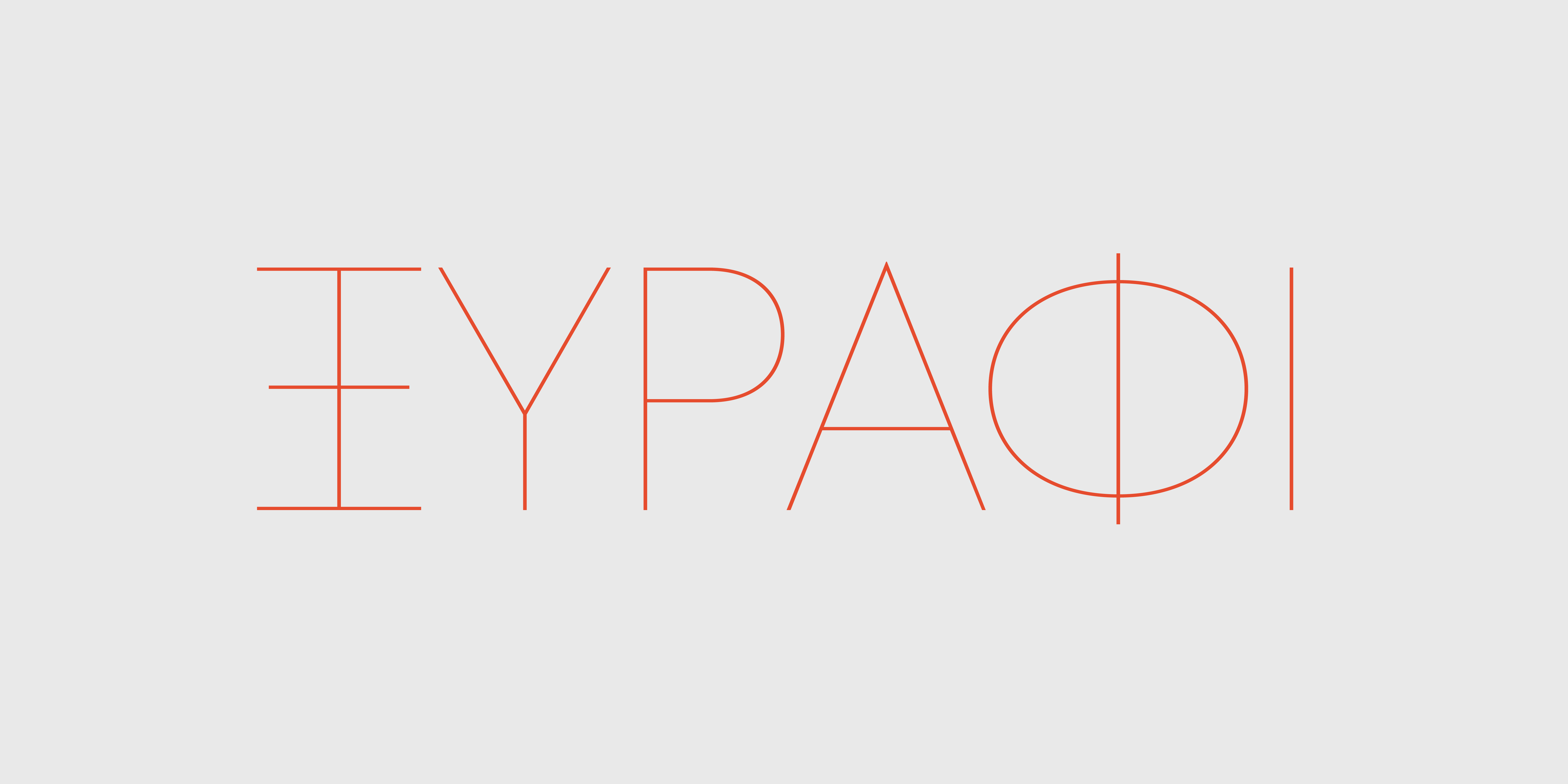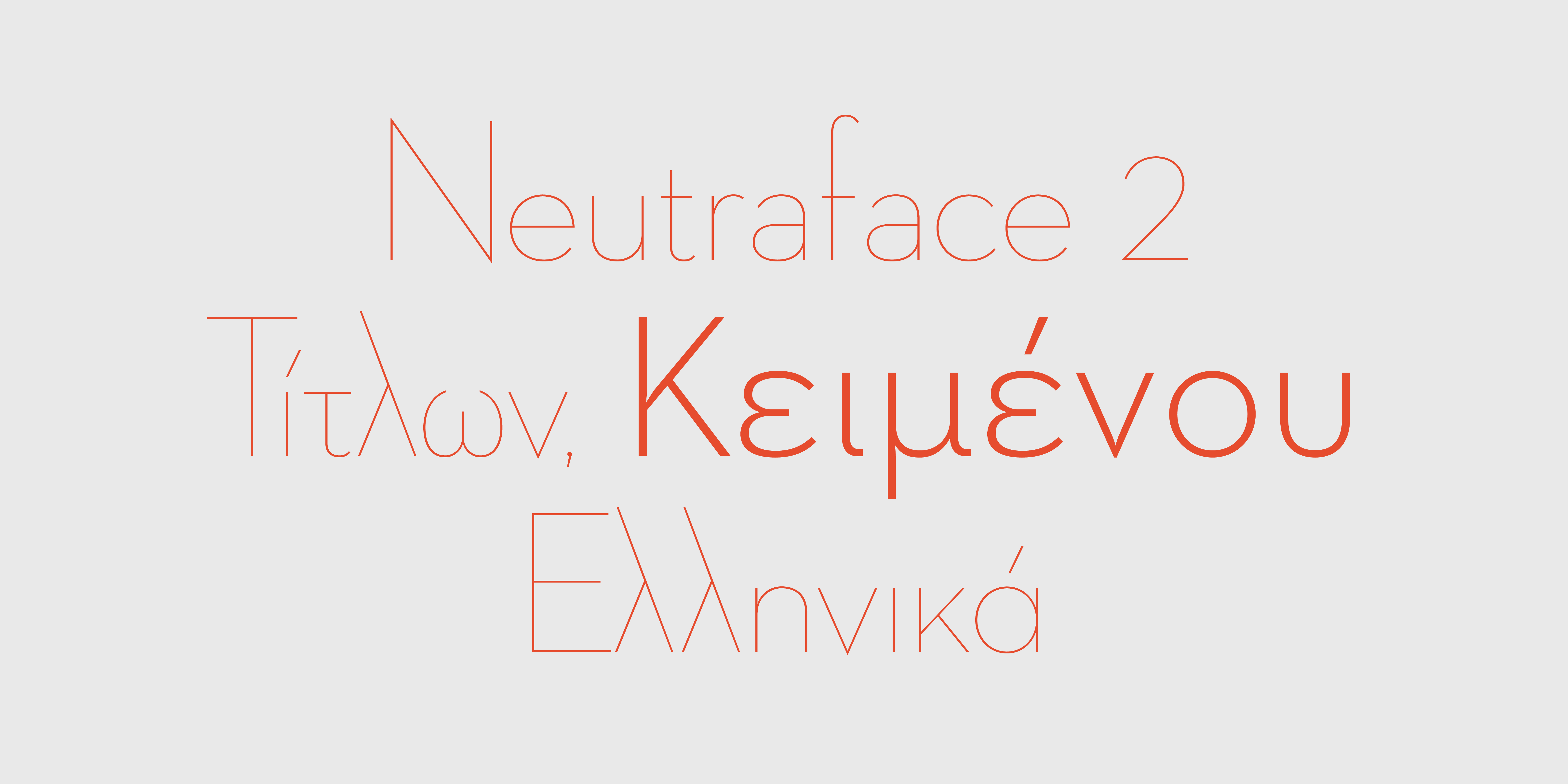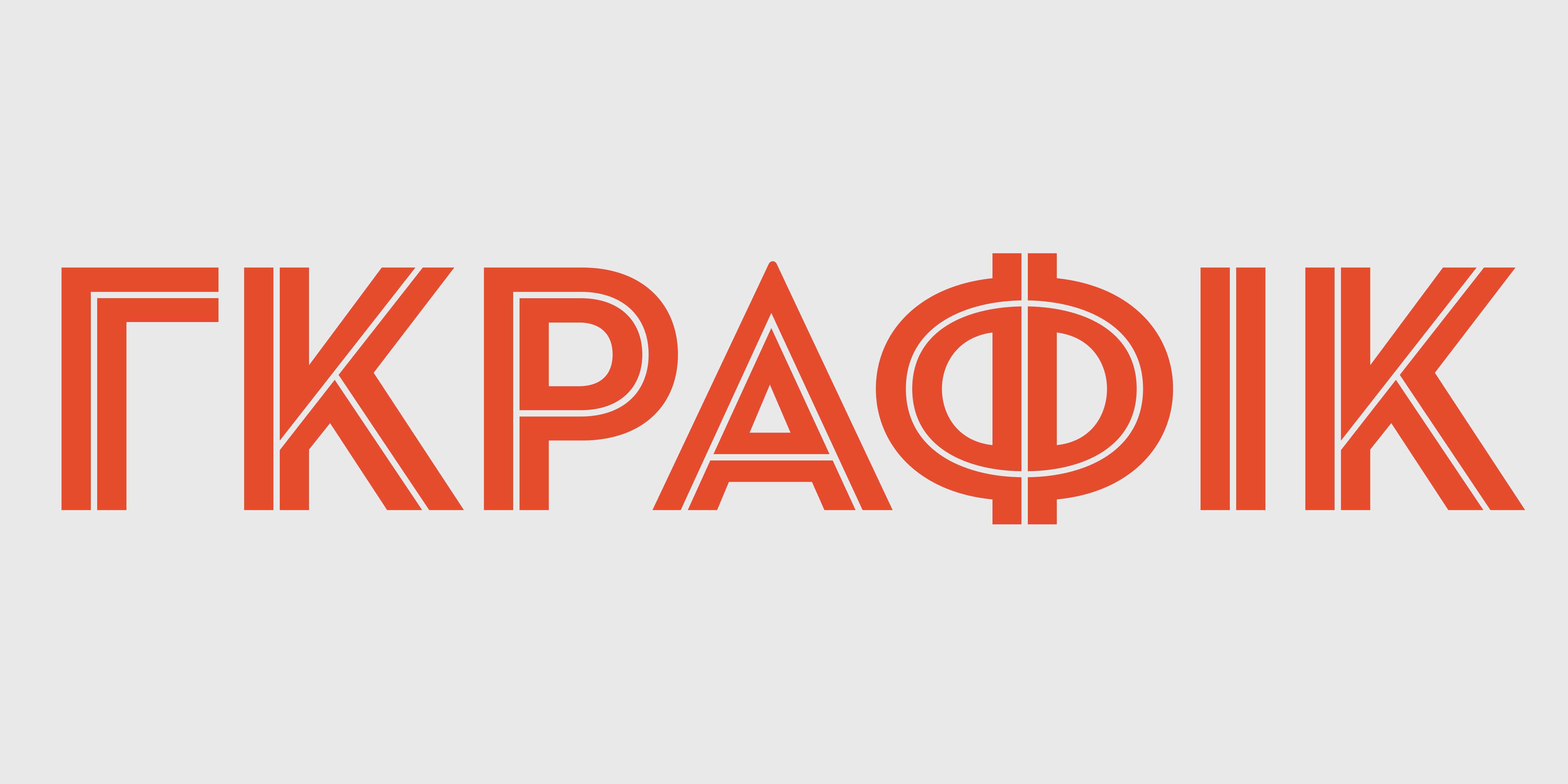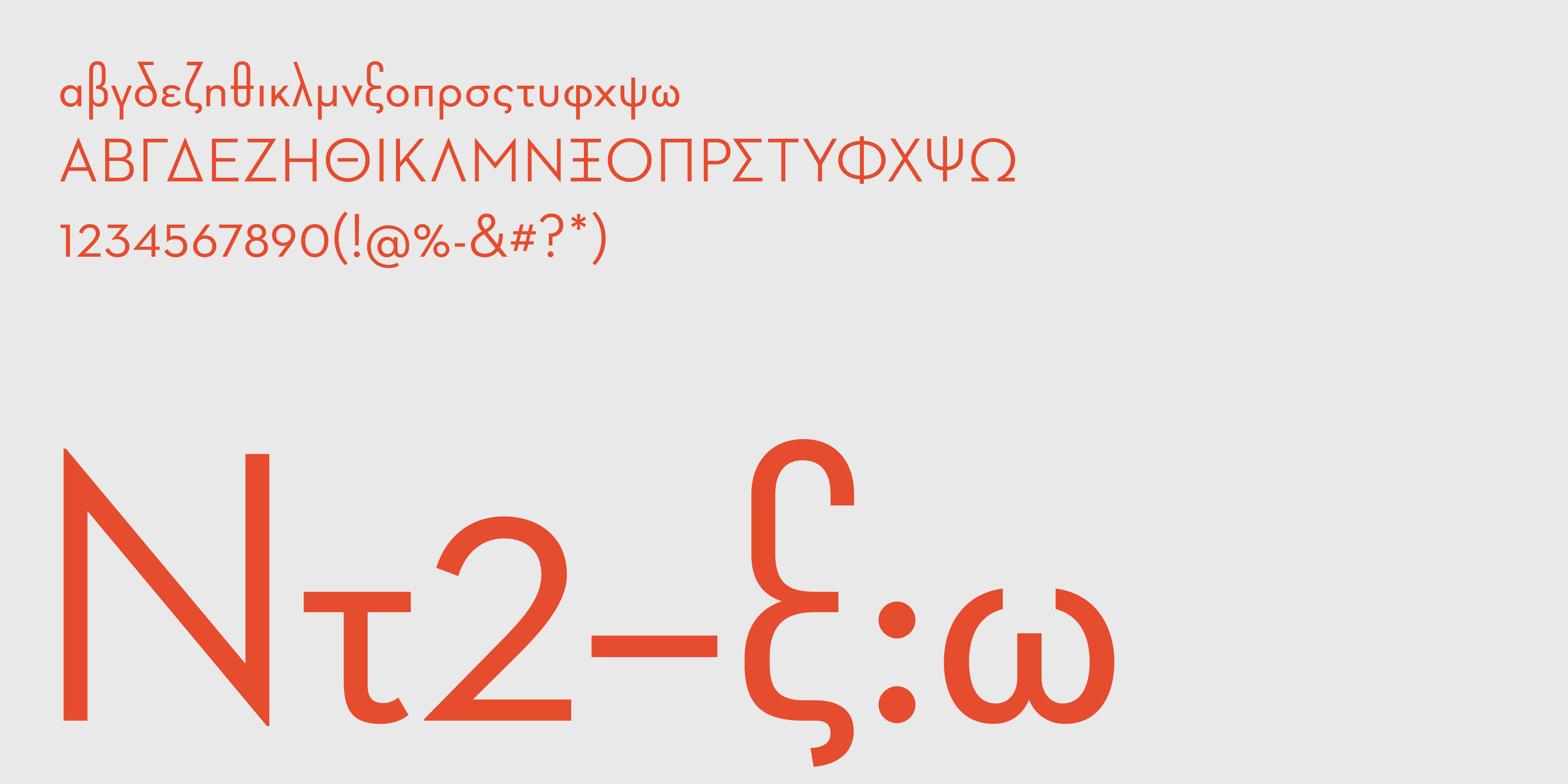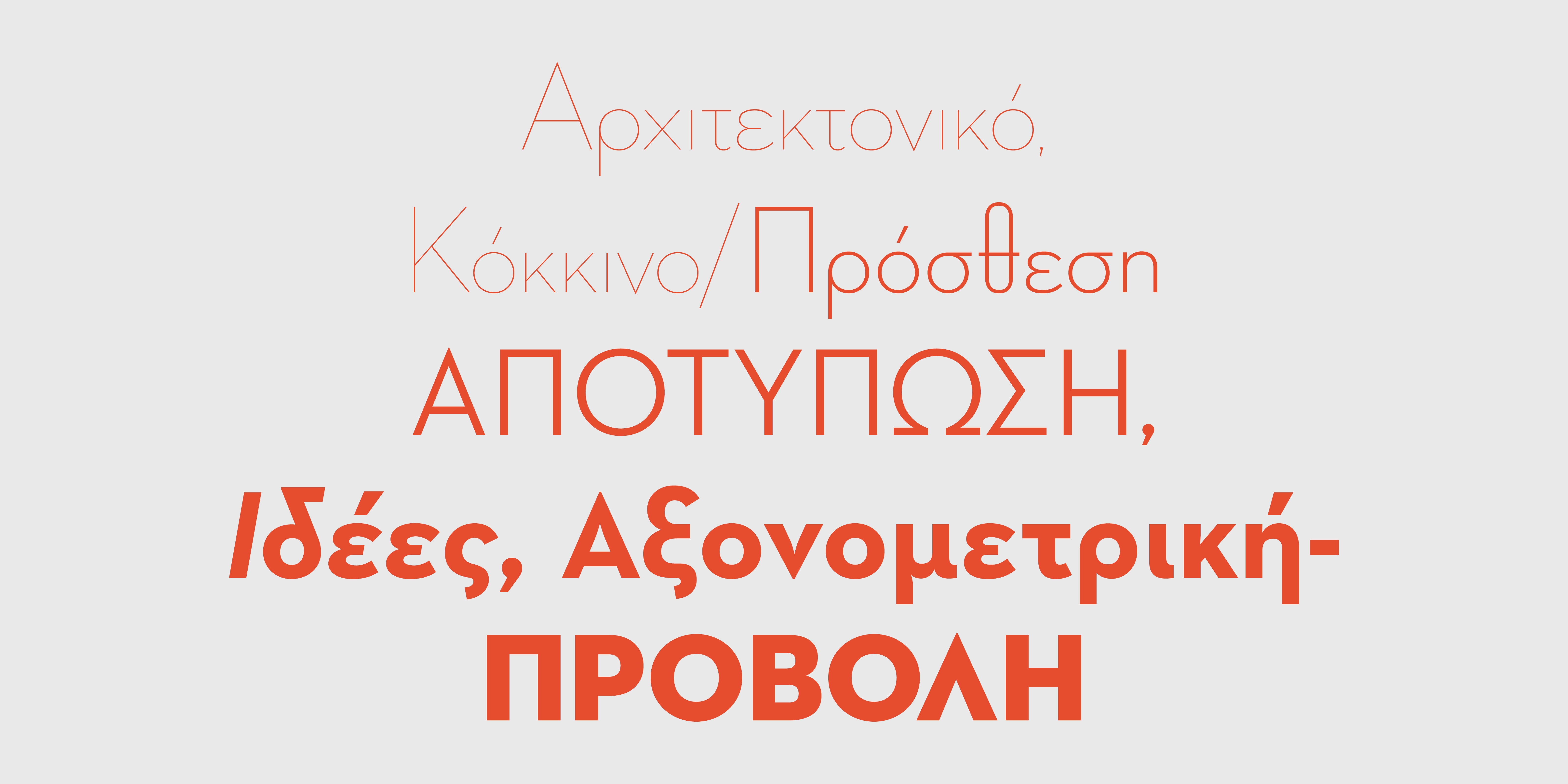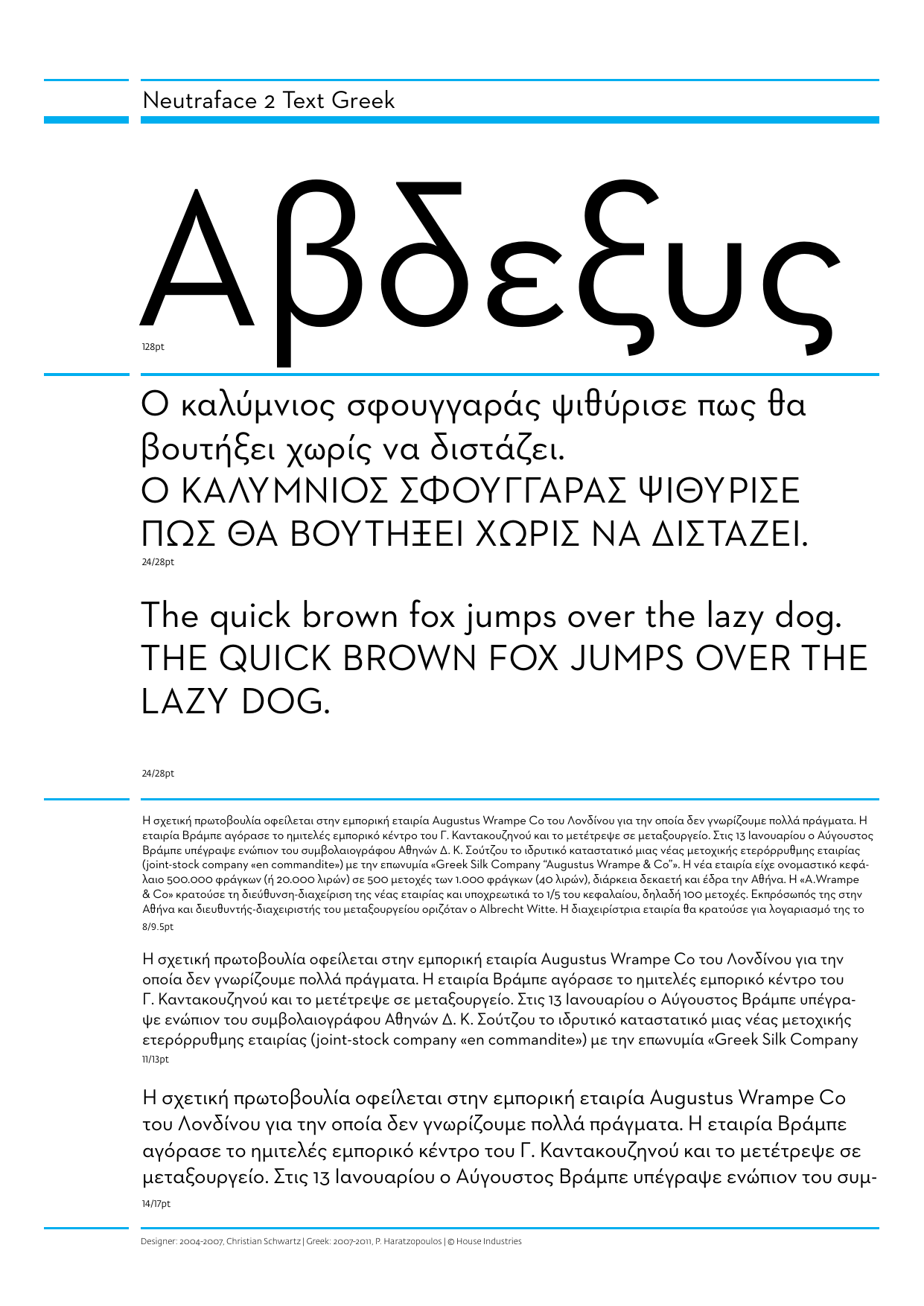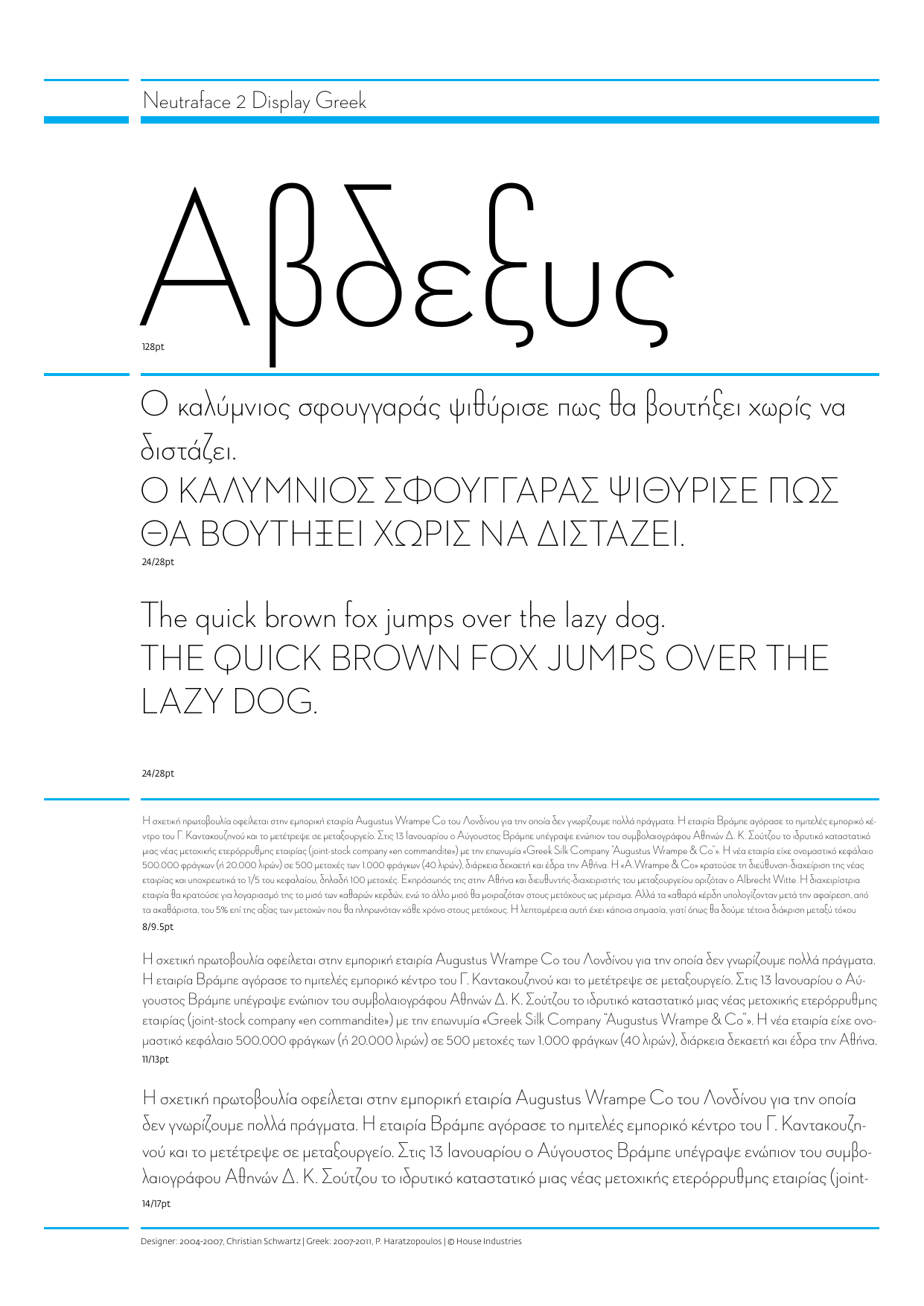
Neutraface 2 Ελληνικά Collection
Neutraface 2 Display Ελληνικά
Thin Light Medi Bold Titl Inline
Neutraface 2 Text Ελληνικά
Light Light Italic Book Book Italic Demi Demi Italic Bold Bold Italic
Το έργο της προσαρμογής των γραμμάτων σήμανσης του αρχιτέκτονα Richard Neutra στην τυπογραφία, ξεκίνησε από την εταιρία House Industries ακολουθώντας πιστά τις συμβουλές του γιου του, Dion Neutra, και μελετώντας σχολαστικά τα αρχεία του γνωστού φωτογράφου Julius Shulman. Με περιορισμένες πηγές εικόνων, ο Christian Schwartz συνέθεσε ένα ολόκληρο αλφάβητο και πρόσθεσε μία συμπληρωματική σειρά πεζών χαρακτήρων που δεν υπήρχε προηγουμένως. Μία εναλλακτική γραμματοσειρά αναπτύχθηκε επίσης, ακολουθώντας ορισμένες μορφές γραμμάτων που συχνά ποίκιλλαν από κτήριο σε κτήριο. Η τελική οικογένεια Neutraface Display περιλαμβάνει πέντε βάρη με κανονικές και εναλλακτικές παραλλαγές και μια μοναδική γραμματοσειρά για τίτλους. H αρχιτεκτονική προέλευση της οικογένειας της γραμματοσειράς οδήγησε στην αρχική δημιουργία της ως μιας γραμματοσειράς για επικεφαλίδες. Ωστόσο, στο πνεύμα της προσέγγισης του Richard Neutra, δημιουργήθηκε μια εκδοχή της Neutraface για κείμενο. Φεύγοντας από τις ασυνήθιστες αναλογίες και το προσεγμένο στυλ της Display έκδοσης, η Neutraface Text διαθέτει μεγαλύτερο ύψος πεζών και μεγαλύτερη αντίθεση στα πάχη για την ενίσχυση της ευαναγνωσιμότητας σε μεγάλα κείμενα. Πιστή στο Διεθνές Στυλ, η Neutraface υποστηρίζει πάνω από εβδομήντα γλώσσες συμπεριλαμβανομένων των συστημάτων γραφής της Κεντρικής και της Ανατολικής Ευρώπης. Στα Ελληνικά, η Neutraface σχεδιάστηκε από τον Παναγιώτη Χαρατζόπουλο, αρχικά για το περιοδικό House & Garden των Εκδόσεων Λυμπέρη. Η δυσκολία για το σχεδιασμό των ελληνικών, εστιάστηκε κυρίως στην απόδοση των πεζών, δεδομένου του πολύ χαμηλού ύψους τους, με το αντίστοιχο πολύ μεγάλο ύψος των ανωφερών στοιχείων. Η εμπορική έκδοση των Neutraface Greek έχει κάποιες επιπλέον σχεδιαστικές διαφοροποιήσεις σε σχέση με την αρχική έκδοση του House & Garden, και περιέχει πλάγιους και πολυτονικούς χαρακτήρες. © House Industries, Σχεδιαστής Christian Schwartz, Ελληνική έκδοση Παναγιώτης Χαρατζόπουλος